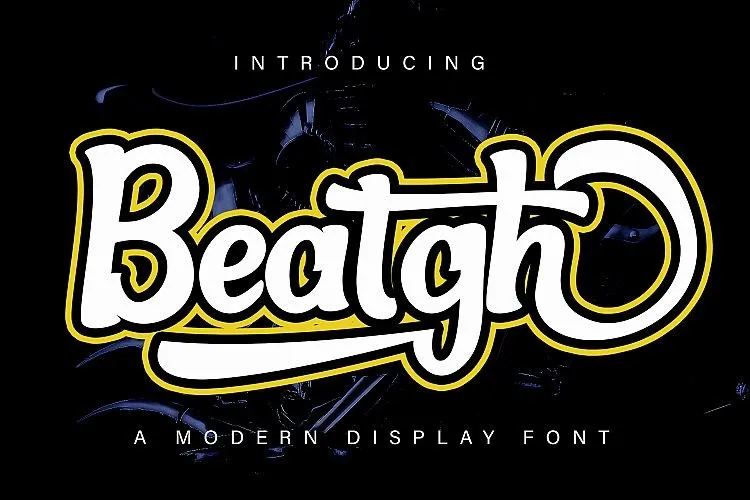
Descubra a fonte Beatgh Bold Script para designers gráficos apaixonados pelo estilo vibrante e único. Esta fonte é uma criação criativa do designer m@graphics, um tipo de script com estilos bold e modernos, perfeitamente adaptado à moda atual dos designers. Beatgh não só oferece a beleza autêntica de uma escrita manual elegante, mas também traz ao seu trabalho uma dose de originalidade e frescura. Ideal para seus projetos personalizados ou promocionais, este tipo de fonte é perfeito para incorporar em desenhos de quadrinhos, logomarcas, materiais de marca, designs de móveis de casa, embalagens de produtos, mugaria, frases e cartazes. Além disso, Beatgh também oferece uma variedade de possibilidades, ideal para nome cards, convites, cartões de agradecimento, e até mesmo capas de livros ou embalagens de sacolas de mão. Uma característica notável da fonte é o seu estilo fresco e divertido, que não só torna seus trabalhos mais atraentes e memoráveis, mas também ajuda a despertar a curiosidade do público. Como uma nova abordagem à escrita manual, Beatgh Bold Script Font traz um novo olhar para o mundo dos têxteis digitais.